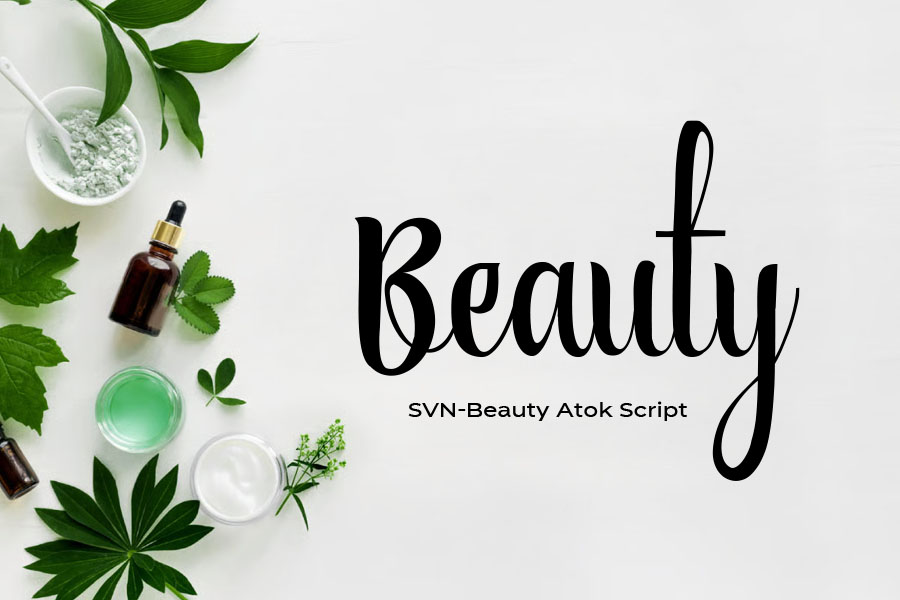
Tác giả Gloow Studio
Việt hóa Team SVN
SVN-Beauty Atok Script là một font chữ viết tay thanh lịch, mang đậm phong cách nữ tính và hiện đại. Được Việt hóa đầy đủ bởi SVN, font không chỉ hỗ trợ tiếng Việt mượt mà mà còn giữ nguyên vẻ đẹp tự nhiên, uyển chuyển của bản gốc do Gloow Studio thiết kế.
Font gây ấn tượng bởi các đường nét mềm mại, cong nhẹ và nối liền tinh tế, mô phỏng nét bút tay của những dòng chữ viết nhanh nhưng vẫn chỉn chu. Từng ký tự được thiết kế có độ nghiêng nhẹ, tạo cảm giác bay bổng, duyên dáng – rất thích hợp cho những thiết kế cần sự gần gũi, cảm xúc và nữ tính.
SVN-Beauty Atok Script là lựa chọn lý tưởng cho các nhà thiết kế khi làm việc với các dự án như: thiệp cưới, thư tay, logo spa hoặc thương hiệu mỹ phẩm, bìa sách văn học, trích dẫn (quotes), hoặc nội dung trên blog và mạng xã hội. Font cũng đặc biệt hiệu quả khi sử dụng trong các thiết kế thủ công, bao bì sản phẩm handmade hoặc đồ trang trí sáng tạo.